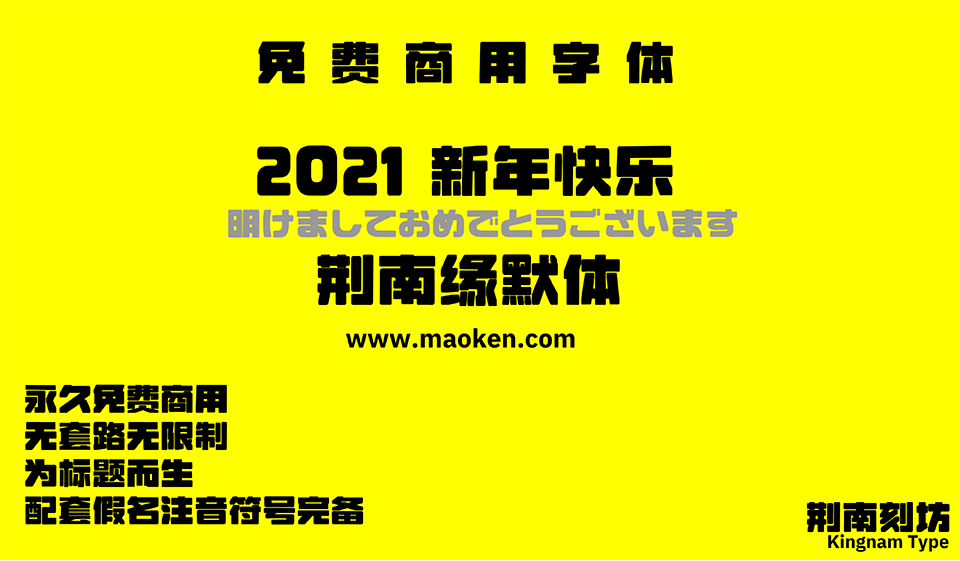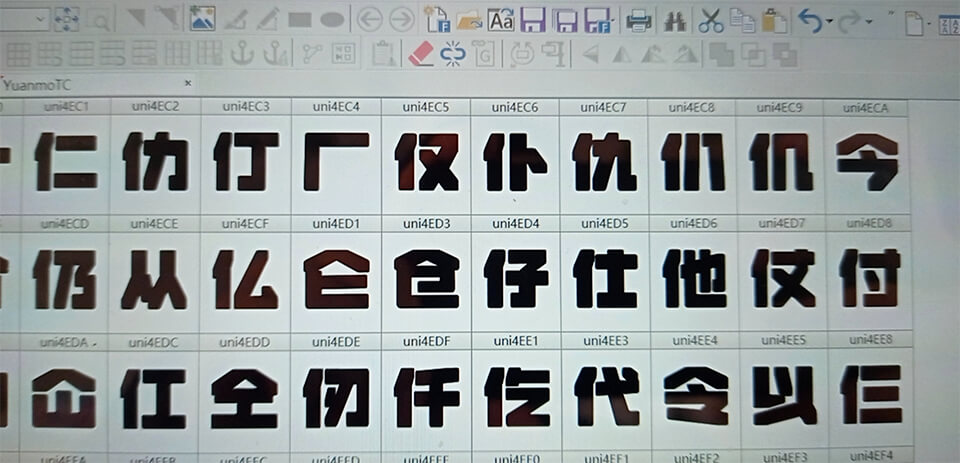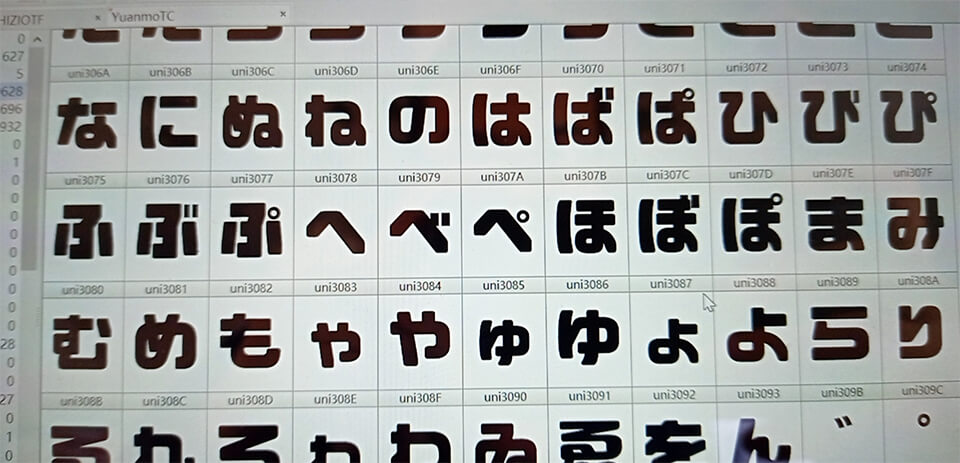
话说猫啃网上已经搜集了301款免费商用中文字体,但是猫啃君一直期待有更多适合标题设计的字体。我希望标题字体能粗一点,更粗一点。之前优设出品的优设标题黑自发布之后受到广泛的欢迎,随处可以。前几天发布的字制区喜脉体也大受欢迎,一下子也成为了猫啃君必装字体之一。
然而踏入牛年,好消息不断。猫啃网又得到独家消息,又一款专为标题设计而生的免费商用字体正在紧张制作中,预计将在今年2月中锂会正式与大家见面。猫啃网有幸得到字体作者@皇帝的新冠的信赖,届时猫啃网也会作为这款字体同步首发渠道之一!
这款字体将命名为荆南缘默体,这款字体的无论是横笔还是竖笔,都会比较粗,特别适合标题、招牌等场景的使用。下面我们一起看率先预览一下这款荆南缘默体的真容吧!
荆南缘默体预计在2月先放出5000字试用版,到2021年中的时候将会放出完整版,配套假名注音符号完备。
这款字体的风格跟日本字体检查站字体风格有点类似,但是笔画会更粗,字形的写法会适合中国大陆的小伙伴,我觉得更漂亮的一款字体。